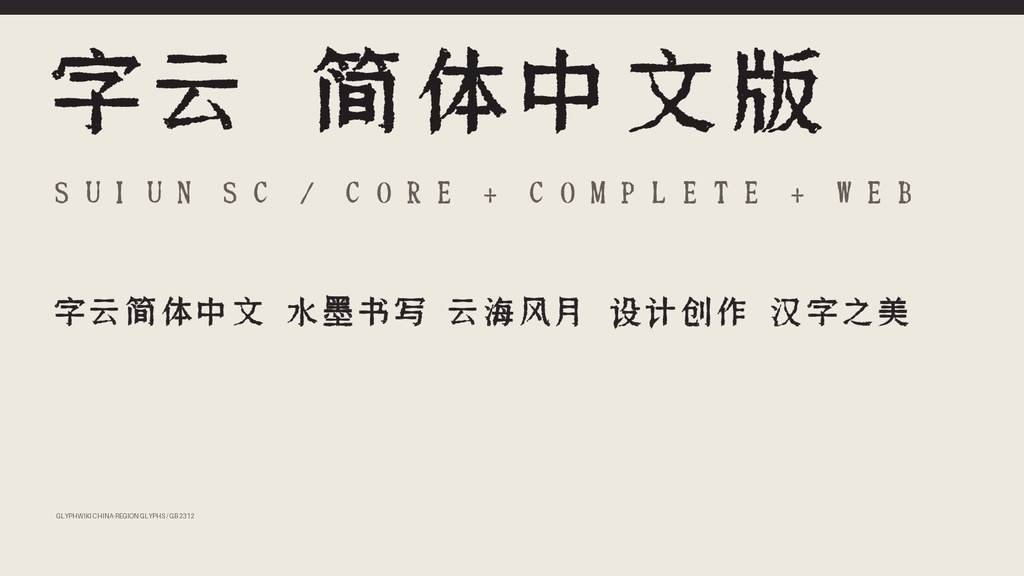
字云 SC Family|简体字6,763字+网页字体
【字云 SC Family / SUIUN SC】 墨迹在字面中晕开、聚散并留下飞白,如云气与水墨在纸上缓慢流动。 这是一款面向简体中文标题设计的水墨风展示字体。 Core 与 Complete 两个版本同包提供,可按作品规模选择轻量版或完整字库。 ■ 价格 1,280日元 ■ 内含版本 ・Core:轻量版,适合网页标题与常用文字 ・Complete:完整字库版,适合海报、视频与大型项目 ■ 格式 TrueType(TTF)/ WOFF2 Windows・macOS / Web ■ 收录 Core:GB 2312 一级汉字3,755字+拉丁字母、数字、半角与全角符号 Complete:GB 2312 全部汉字6,763字 Complete 每款共7,542个字码(包含空格) 另含779个拉丁字母、数字、半角与全角符号 ■ 特点 ・水墨晕染、飞白与云雾般的轮廓 ・汉字、英文字母、数字和符号保持统一的墨迹表现 ・Core / Complete 可根据容量与用途灵活选择 ・同时提供桌面字体与网页字体 ■ 推荐用途 东方幻想作品、游戏标题、影视字幕、书籍封面、音乐封面、海报、品牌标志、网页主视觉 ■ 使用许可 可用于个人及商业项目。可用于标志、视频、游戏、印刷品、直播素材、同人及商业作品。 无需署名。禁止重新分发、共享或转售字体文件。 详细条款请查看ZIP内的使用许可。 ※本字体适合标题、标志和大字号视觉设计,长篇正文请先确认可读性。